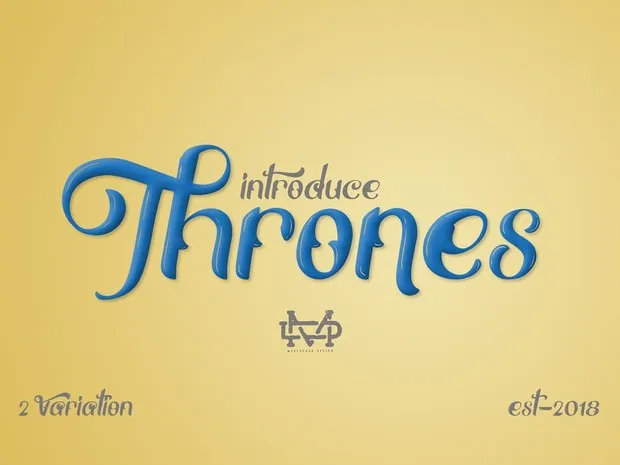
Thrones Font – Fonte Grátis
Thrones Font
Thrones é uma fonte display que promete surpreender os designers devido a sua design elegante e personalidade robusta. Feito pelo designer madeDeduk, essa fonte se destaca com seu ar deslumbrante e força sofisticada, tornando-a um excelente complemento para qualquer projeto visual. Seja para criar uma identidade visual única ou adicionar um toque distintivo em designs de newsletter, Thrones oferece a oportunidade de capturar o olhar do público com sua elegância assertiva. Esta fonte é perfeita para aqueles que buscam um estilo marcante e sofisticado, tornando-a um recurso indispensável para designers criativos em todo o Brasil.